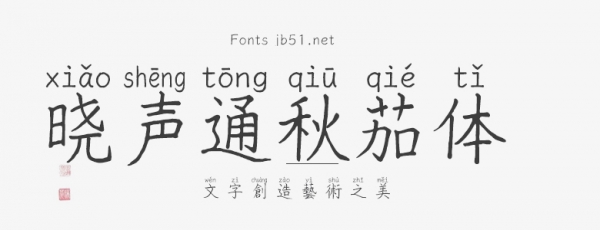
曉聲通「秋茄體」是開(kāi)源免費(fèi)的手寫(xiě)字型,筆形符合教學(xué)《教師手冊(cè)》,由教育全文注音辭典 「曉聲通 https://toneoz.com/imez」開(kāi)發(fā) 。
「手寫(xiě)字型」常用于詩(shī)詞、歌曲、人物獨(dú)白或?qū)υ?用以提示讀者此段文句建議「以人文角度來(lái)思考體會(huì)」。
市面上有許多優(yōu)美的手寫(xiě)字型:有些草書(shū)字型筆跡奔放、有些美術(shù)字型筆觸可愛(ài)、部分書(shū)寫(xiě)時(shí)會(huì)參雜不同教育標(biāo)準(zhǔn)或通俗寫(xiě)法、有些實(shí)作四千~九千常用字而有缺字遺憾…以上多少在教學(xué)時(shí)帶來(lái)困擾。
為了輔助教材制作,「曉聲通國(guó)語(yǔ)注音字典」開(kāi)發(fā)了「秋茄體(水筆仔)」,來(lái)幫助老師們輕松創(chuàng)作教案。